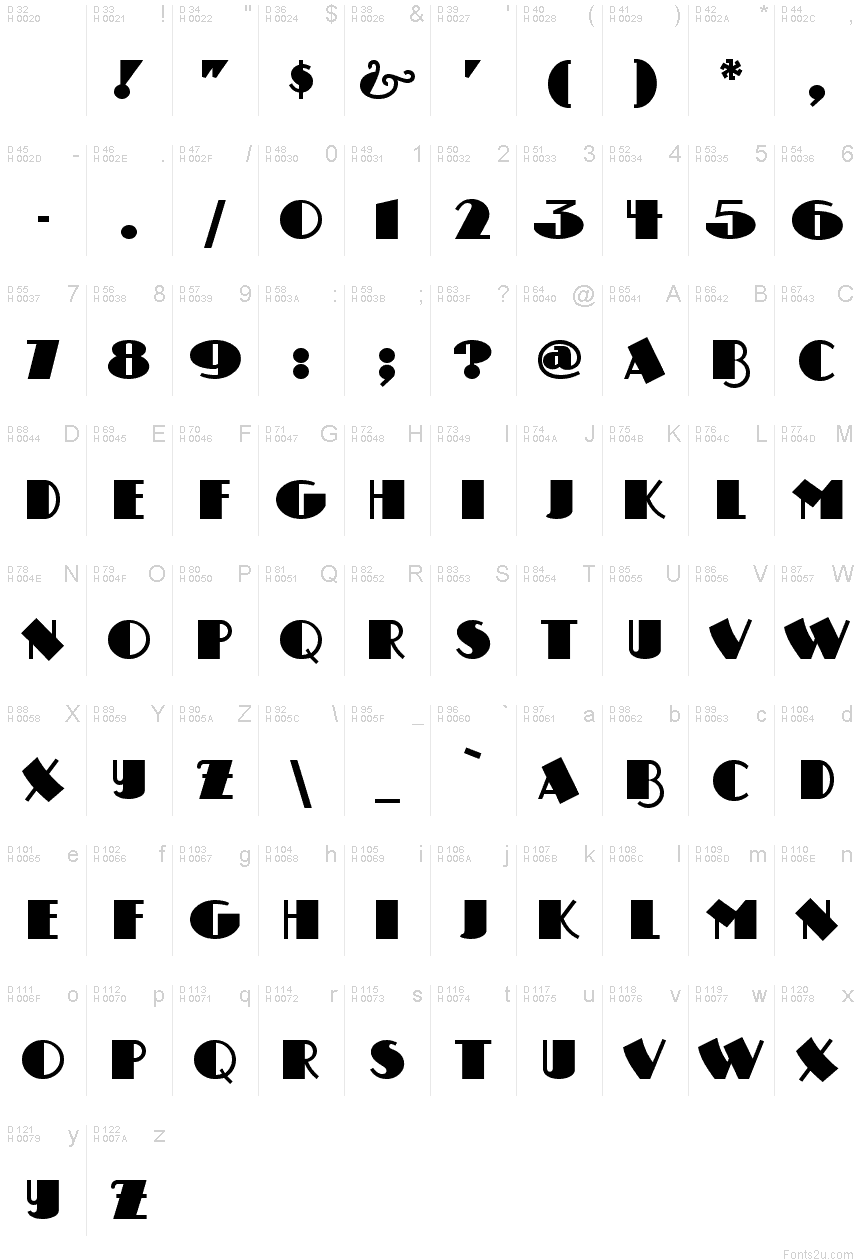
DrumagStudioNF od Nicka Curtisa z Nick's Fonts to bezszeryfowy krój w stylu retro, wyróżniający się ostrymi, geometrycznymi cięciami, masywnymi czarnymi kształtami i wyrazistym rytmem Art Déco. Połączenie okrągłych obłości z kanciastymi wycięciami nadaje mu filmowy, wręcz plakatowy charakter – bardziej wyrafinowany niż zabawny.
DrumagStudioNF świetnie sprawdza się wszędzie tam, gdzie potrzebujesz błyskawicznego efektu: w logo, na okładkach płyt, w menu, na opakowaniach, plakatach, szyldach czy w tytułach. Ten darmowy font lubi przestrzeń, więc zestaw go z prostym krojem pisma i pozwól, by jego śmiała sylwetka grała główną rolę.